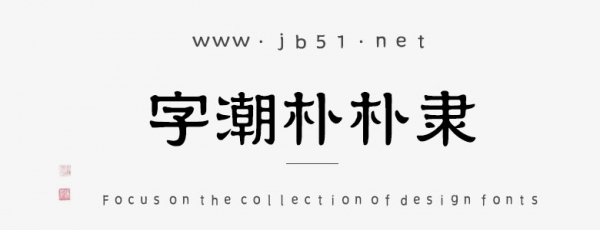
字潮樸樸隸是由字潮字庫(kù)出品的字體,這款字體筆觸適中,端正大氣,具有很好的視覺(jué)感,適合應(yīng)用于藝術(shù)設(shè)計(jì)、平面宣傳設(shè)計(jì)、網(wǎng)頁(yè)設(shè)計(jì),書(shū)法字帖等領(lǐng)域,需要的朋友可以前來(lái)本站下載。